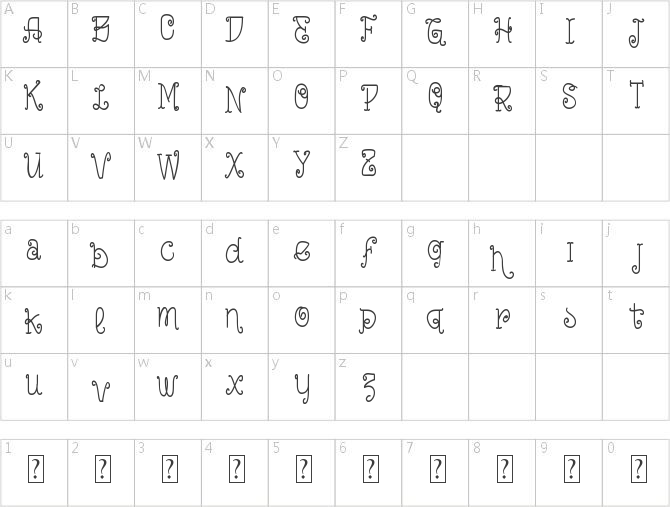
Vtks Love is EveryThing 詳情頁
Vtks Love is EveryThing字體字庫是一款讓人賞心悅目、百看不厭的英文字體,適合各類廣告和產(chǎn)品包裝設(shè)計應(yīng)用,字體大小0.03MB,格式為ttf字體,上傳用戶是文生電腦,作者/版權(quán)方為未知